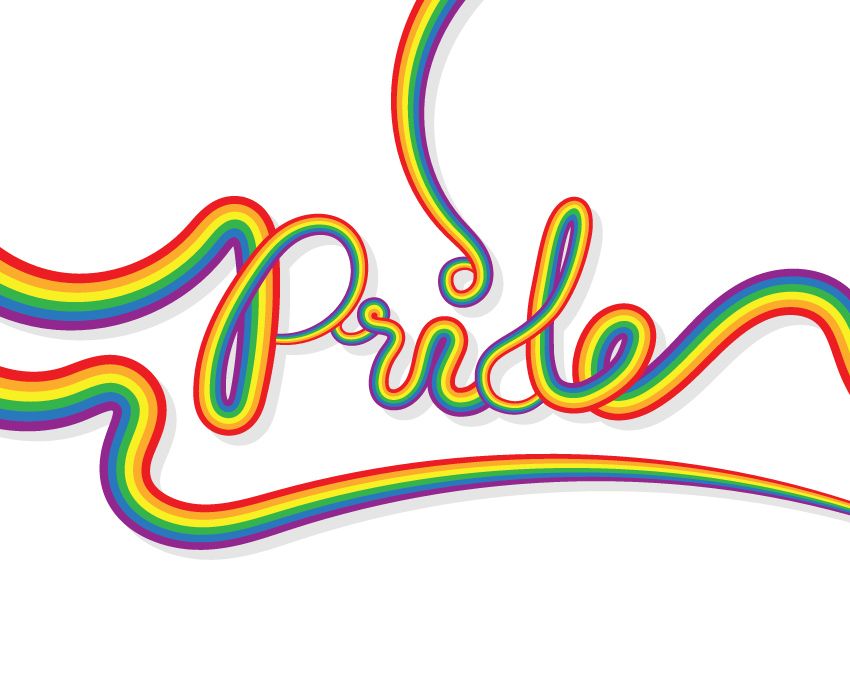
La verdad eso no esuna tipografía, es un trabajo hecho con herramientas del programa ya sea photoshop o illustrator, como patterm, pinceles montando bajo una muestra. Aquí te envio una idea mas o menos similar a lo que necesitas. Saludos. https://bit.ly/2UREBd9